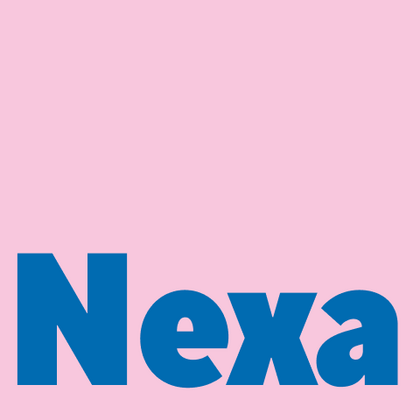
Шрифты похожие на Nexa
Если вы в поисках современного геометрического гротеска, коллекция TypeType станет отличным решением. В подборке представлены шрифты, которые могут стать отличной альтернативой шрифту Nexa, предлагая аналогичную эстетику. Как и шрифт Nexa, они идеально подходят для креативного брендинга, веб-дизайна и интерфейсов, рекламных кампаний и корпоративных проектов. Гарнитуры TypeType — это современные решения для проектов, где важны четкие линии и универсальность.
Если вы устали от «заезженных» шрифтов и ищете гарнитуры, похожие на Nexa, ознакомьтесь с нашими лучшими альтернативами Nexa. Это шрифты, которые имеют близкие характеристики, но в то же время обладают новыми уникальными особенностями дизайна. Например, относятся к той же категории шрифтов, подходят для тех же целей и имеют похожие черты, но отличаются в деталях или пропорциях.
Найдите отличную замену Nexa и попытайтесь имитировать похожее настроение, передать нужное вам ощущение, используя его в своих проектах. Каждый шрифт, представленный на этой странице, является двойником шрифта Nexa, фактически его полным аналогом.
TT Fellows — гуманистический гротеск с механистическими мотивами. Открытые формы, дружелюбно-нейтральный характер тонких весов и ещё более мягкий характер в жирных начертаниях.
TT Travels Text — геометрический гротеск с широкими пропорциями. Основные визуальные отличия TT Travels Text — достаточно широкие пропорции и немного сквадраченные формы овалов.
TT Chocolates — изящный гуманистический гротеск сo сбалансированными пропорциями, близкими к классическим. Шрифт с приятным дружелюбным характером, который интуитивно воспринимается как что-то знакомое.
TT Firs Text создавался на основе обновленной в 2023 году гарнитуры TT Firs Neue. Мы сохранили эстетику скандинавского минимализма, но полностью перерисовали все выразительные элементы, сделав их более мягкими и традиционными.
TT Wellingtons — это гуманистический гротеск, формы которого отсылают к движению ширококонечного пера. Пластичные линии букв обновлённой гарнитуры, присущие английским гуманистическим шрифтам XX века, выглядят актуально и живо в современных дизайнерских проектах.
TT Commons™ Classic является универсальным гротеском с минимальным контрастом штрихов, закрытой апертурой и геометрическими формами знаков. Дизайн гарнитуры разрабатывался для максимально широкого круга задач, с которыми обязан справляться любой качественный корпоративный шрифт.